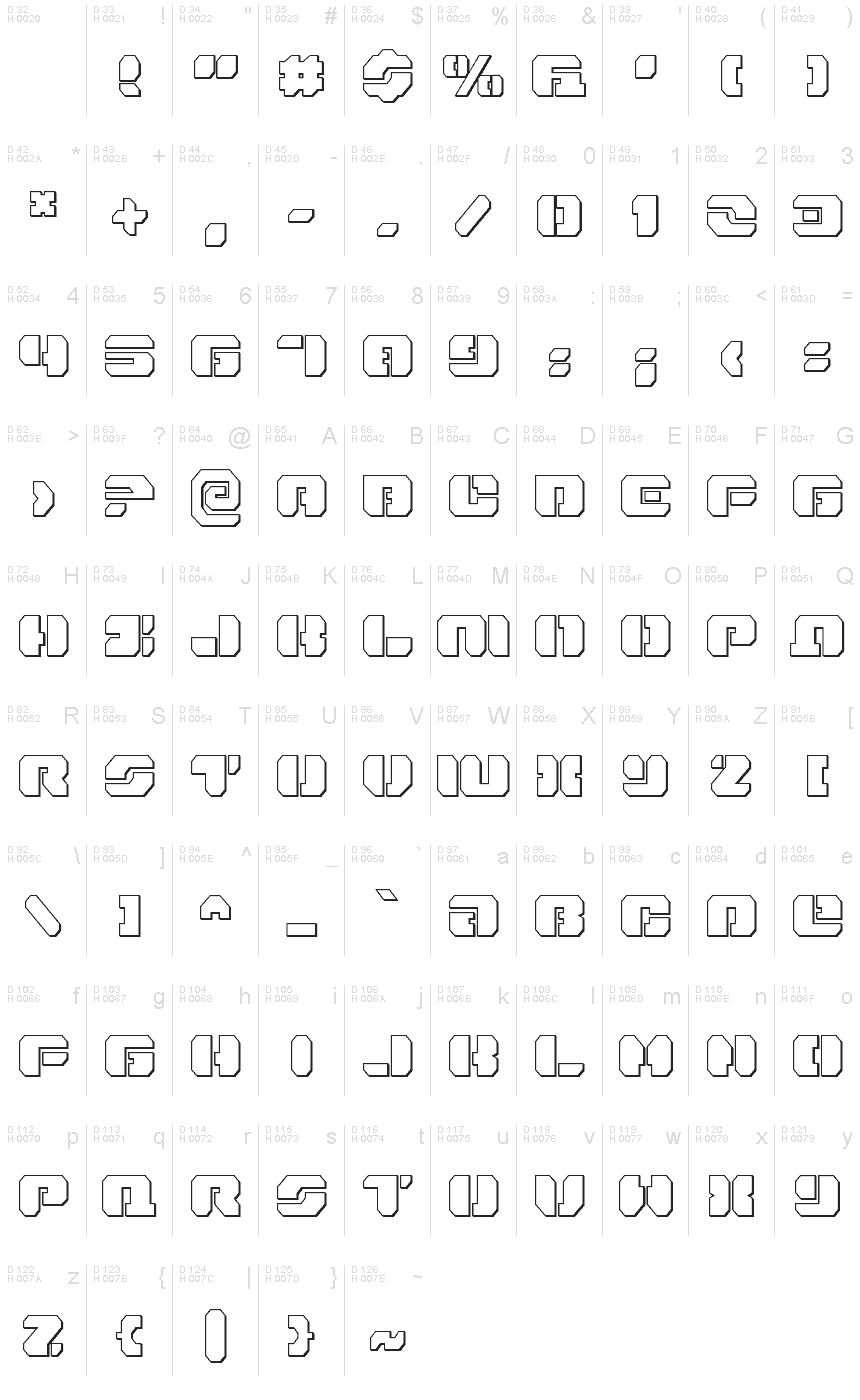
Dan Stargate Outline di Iconian Fonts è un font display gratuito dal look futuristico e con una decisa attitudine sci-fi. Le lettere sono costruite con solidi blocchi geometrici dagli angoli smussati, linee interne sottili e un ritmo modulare che ricorda le scritte sulle astronavi e i titoli dei giochi arcade.
È perfetta per loghi di videogiochi, titoli di poster, schermate per lo streaming, copertine di album e grafiche per eventi tech, dove il contorno segmentato conferisce alle parole brevi una presenza forte e ingegnerizzata. Essendo un font gratuito, funziona benissimo anche per monogrammi e loghi in stile badge, soprattutto quando si desidera che le maiuscole trasmettano un aspetto più architettonico e meno raffinato.